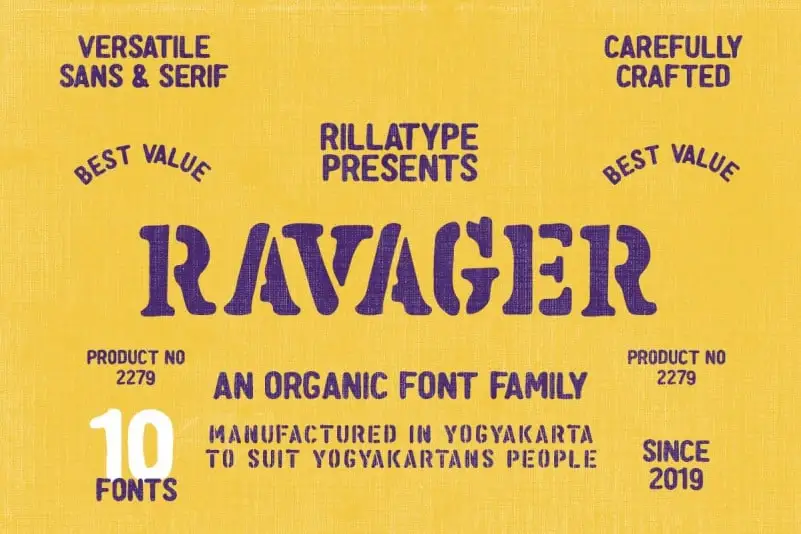
Ravager Display Font – Fonte Grátis
Ravager Display Font
A fonte Ravager Display é uma escolha ótima para quem procura estilo militar tanto no formato moderno quanto clássico. Com seu design orgânico que inclui 10 tipos diferentes, você tem um leque amplo de opções que não só tornam o projeto mais atraente, mas também adiciona um toque único e versátil. Suas variedades entre sans-serif e serif são especialmente adequadas para criação de logomarcas, escrita à mão ou mesmo design de roupas, garantindo que sua identidade seja visualmente memorável. O suporte a múltiplos idiomas torna o Ravager Display Font uma ferramenta poderosa para designers em busca de flexibilidade e versatilidade. Este conjunto de fontes moderno e vintage não só atende às necessidades dos projetos militares, mas também se estende aos mais diversos setores do design gráfico, desde a criação de logotipos até o design de roupas personalizadas. Incrivelmente versátil, o Ravager Display Font é perfeito para quem deseja incorporar um toque único e orgânico em seus projetos. Uma vez que a fonte foi criada por designers na 99designs, você pode esperar qualidade e diversidade de opções quando escolher entre seu leque de fontes diferentes.